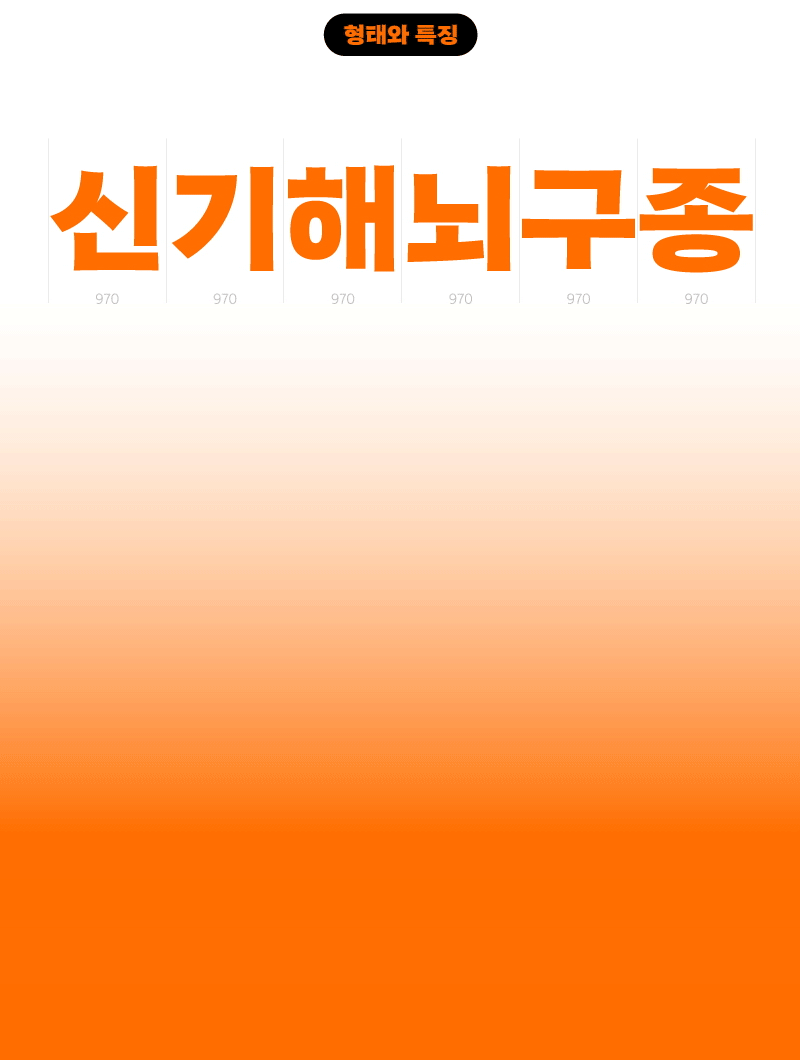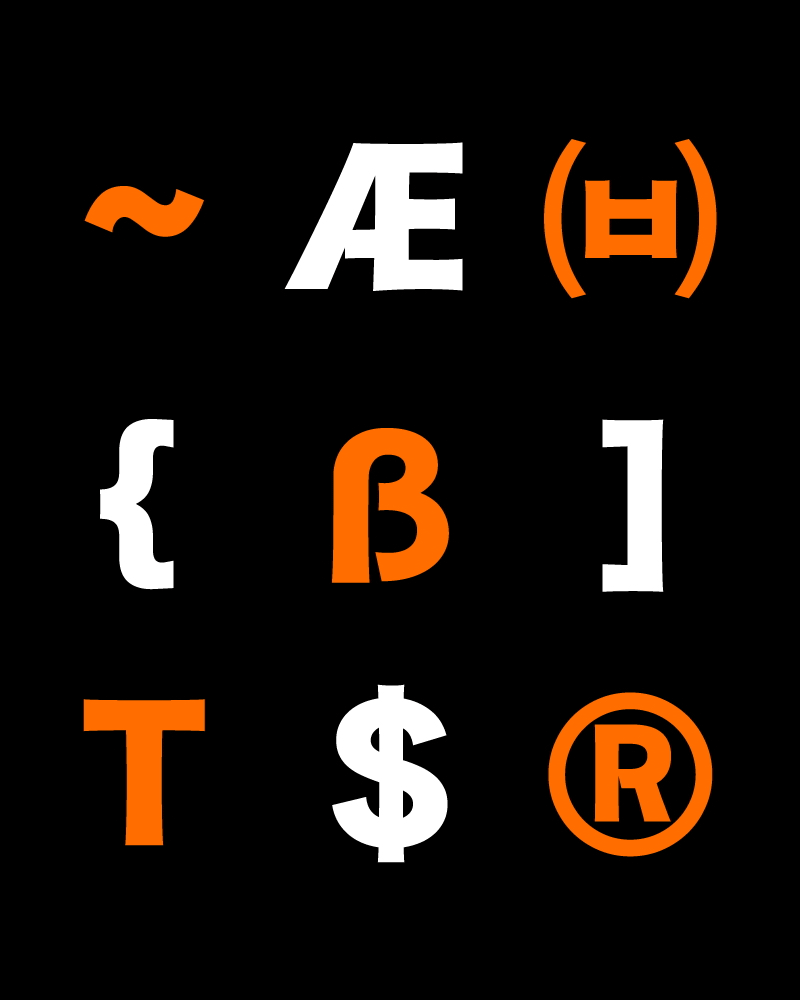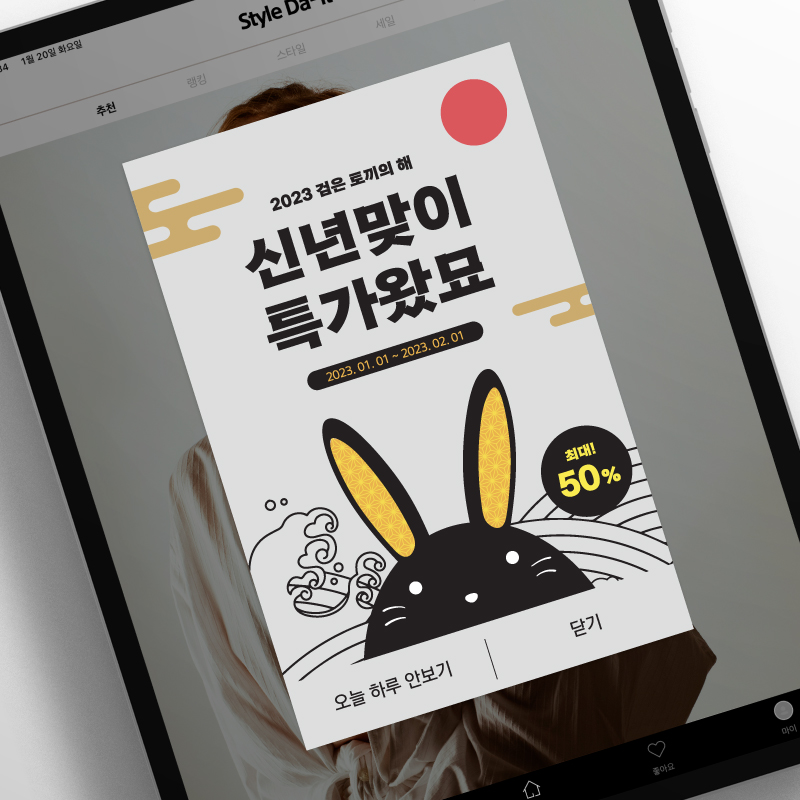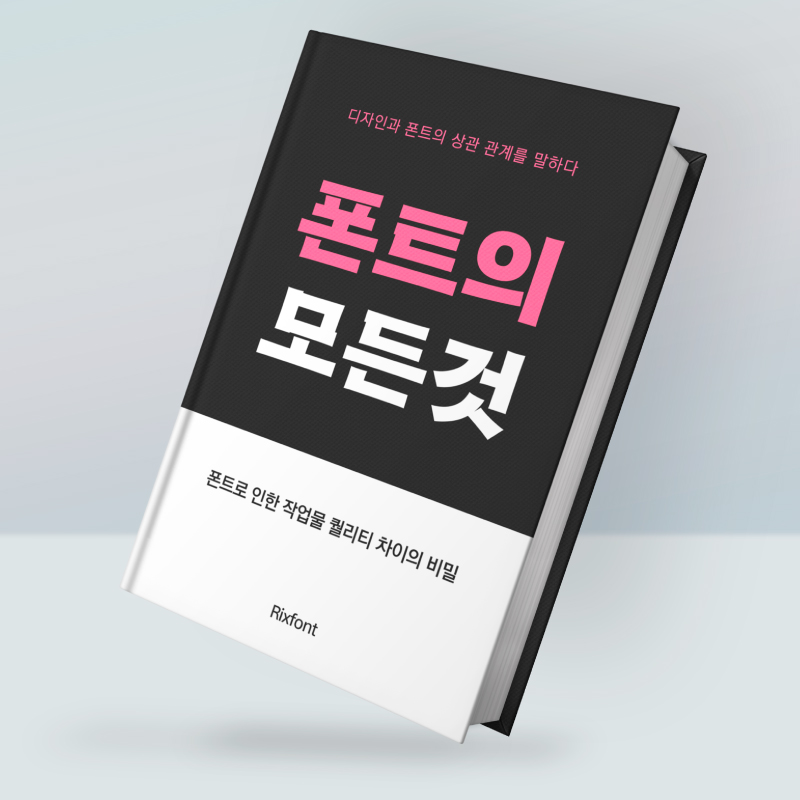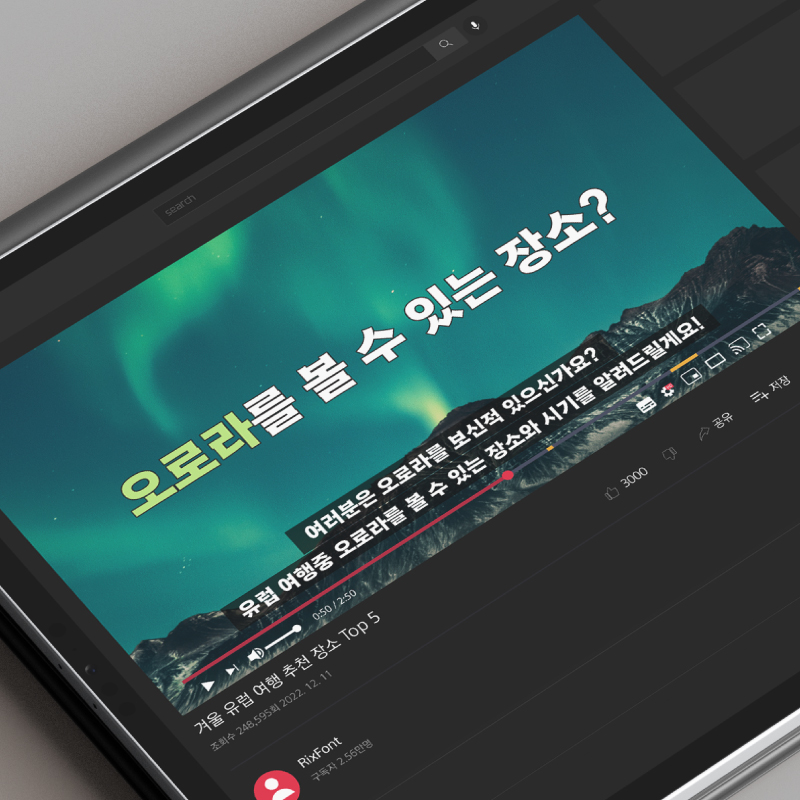
Rix편고딕
1 종 - Regular텐션감이 있는 형태로 활기를 띠며 단단한 인상을 가진 헤드라인 글꼴입니다.
손글씨의 성격을 반영한 거친 필력과 날카로운 크랙이 특징으로 강한 어조에 잘 어울립니다.
여유로운 골격과 두꺼운 획으로 제목용으로 활용하기에 좋은 서체입니다.